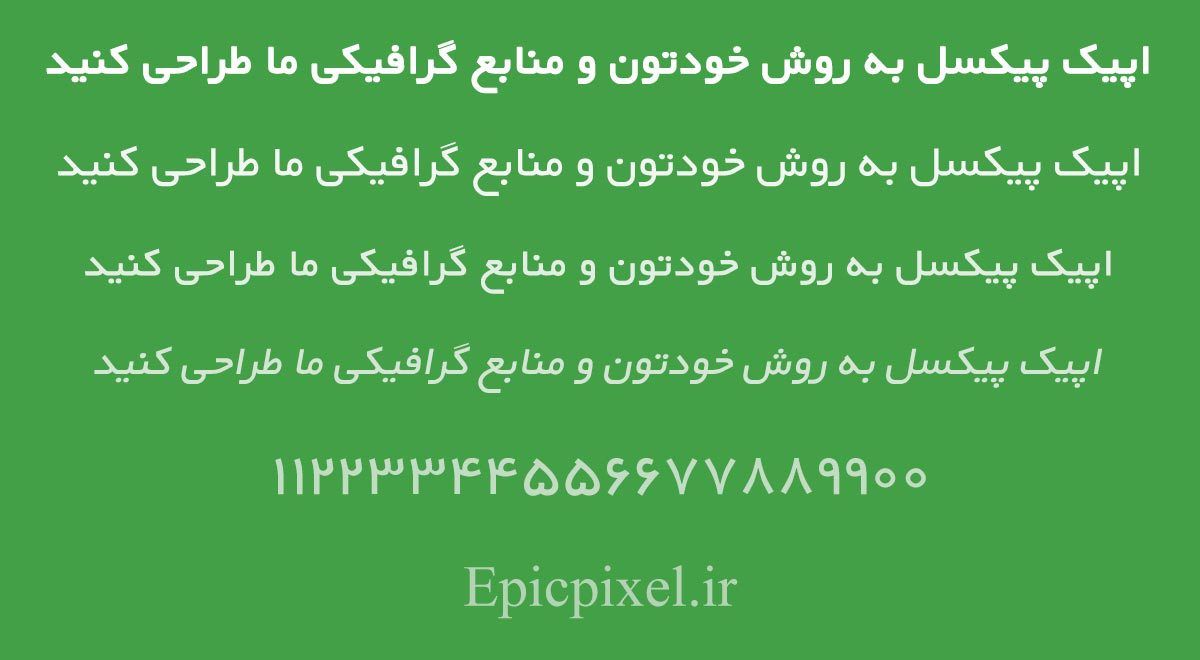
مجموعه کامل فونت های سری IPT (+64 فونت)
مجموعه کامل فونت های سری IPT (Iranian Professional Typefaces) شامل ۶۴ فونت فارسی رایگان است که توسط شرکت IPT طراحی و تولید شده اند. این فونت ها، مانند فونت F، عمدتاً برای حل مشکل فارسی نویسی در نرم افزارهایی که به صورت مستقیم از زبان فارسی پشتیبانی نمی کنند (مانند اتوکد) طراحی شده اند. برای استفاده از این فونت ها در چنین محیط هایی، نیاز به یک برنامه فارسی نویس واسط (مانند کدفا یا فارسی نویس IPT 5) وجود دارد. فونت های IPT به دلیل کیفیت بالا و تنوع، محبوبیت زیادی در میان طراحان گرافیکی و تولیدکنندگان محتوا دارند.
فونت های IPT (Iranian Professional Typefaces) مجموعه ای از قلم های فارسی هستند که با هدف ارائه راه حلی برای تایپ زبان فارسی در محیط هایی که پشتیبانی بومی از زبان فارسی ندارند، توسعه یافته اند. این مجموعه شامل ۶۴ فونت متنوع است که امکانات گسترده ای را برای کاربران فراهم می کند.
کیفیت و تنوع: فونت های IPT به دلیل کیفیت بالا و تنوع زیاد در سبک های مختلف، در بین طراحان گرافیکی و تولیدکنندگان محتوا بسیار محبوب هستند. این مجموعه گزینه های متعددی را برای پروژه های مختلف، از متن های رسمی تا طرح های خلاقانه، ارائه می دهد.
دانلودکاربرد در برنامه های متنوع: فونت های IPT علاوه بر کاربرد تخصصی در نرم افزارهایی مانند اتوکد، در برنامه های مختلف طراحی گرافیکی مانند Adobe Photoshop، Adobe Illustrator، CorelDRAW و همچنین در نرم افزارهای تولید محتوا مانند Microsoft Word و PowerPoint نیز قابل استفاده هستند و به زیبایی و خوانایی متون فارسی در این برنامه ها کمک می کنند.
کاربردهای مجموعه فونت های سری IPT
مجموعه فونت های سری IPT برای رفع نیازهای تایپ و نمایش فارسی در سناریوهای مختلف، به ویژه در محیط هایی که پشتیبانی بومی از فارسی ندارند، مناسب است:
- نرم افزارهای طراحی مهندسی (مانند اتوکد): امکان فارسی نویسی در محیط های CAD با کمک ابزارهای فارسی نویس.
- نرم افزارهای گرافیکی: افزایش گزینه های فونت فارسی برای استفاده در فوتوشاپ، ایلاستریتور، کورل دراو و سایر برنامه های گرافیکی.
- اسناد اداری: استفاده در مایکروسافت ورد و پاورپوینت برای ایجاد اسناد فارسی با ظاهر حرفه ای.
- محیط های خاص و قدیمی ویندوز: راه حلی برای تایپ فارسی در برنامه هایی که از یونیکد فارسی به درستی پشتیبانی نمی کنند.